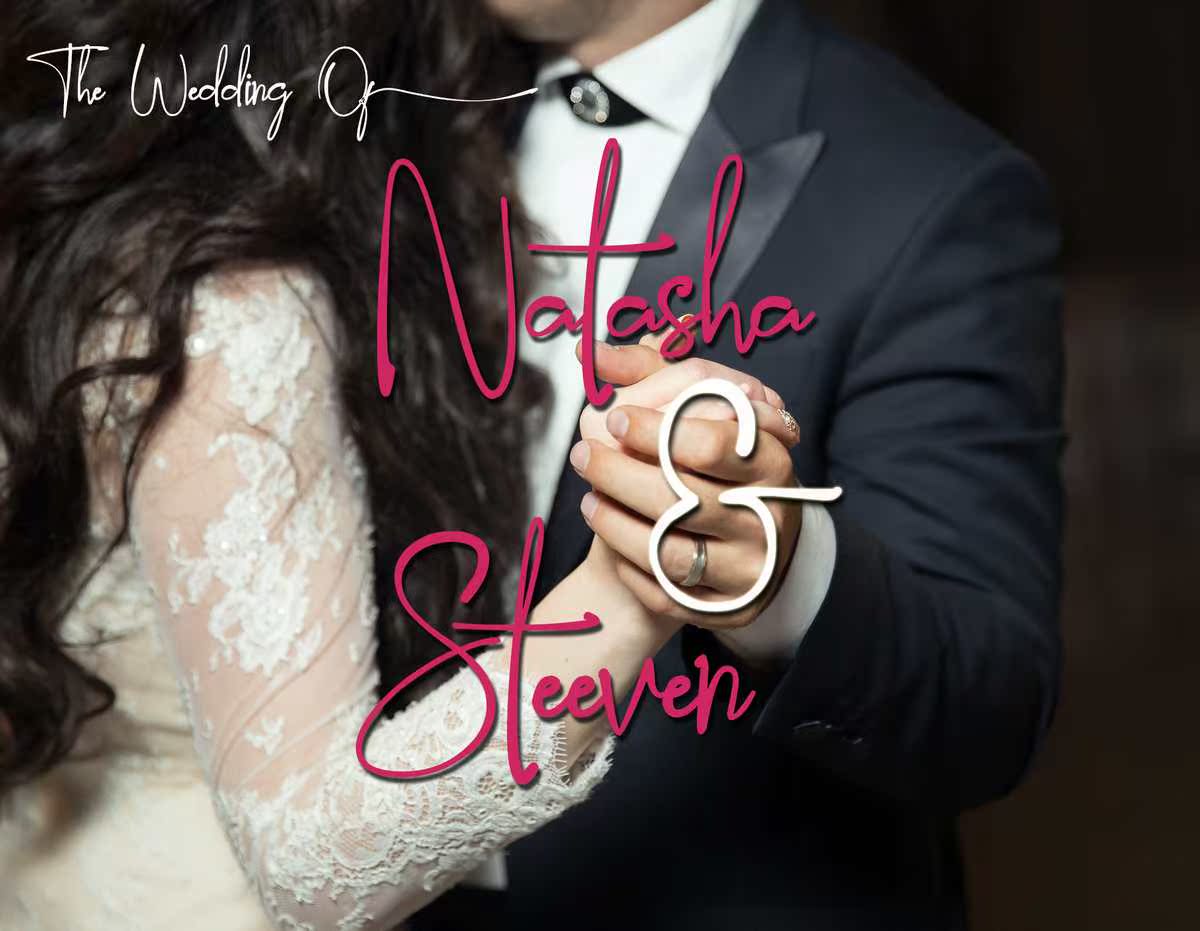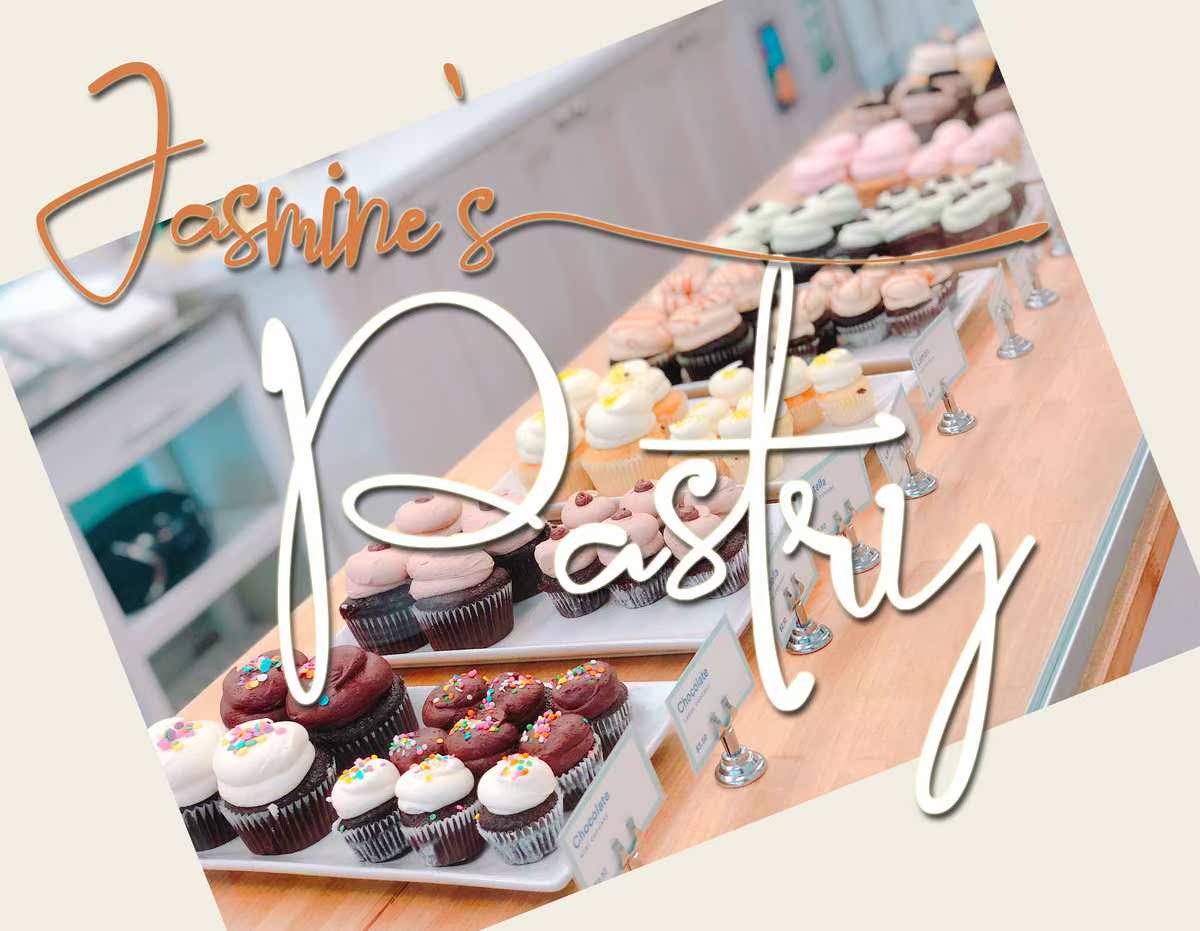
QuickyLove是由HizartDesign编写的现代手写字体。它可以准确地手写字母,让您的设计具有优美的文字,让您的设计更具吸引力。QuickyLove是徽标、贺卡、包装设计、耐磨性、工艺设计、任何项目、书名、婚礼宣传、包装的完美之选,还有更多。QuickyLove是由HizartDesign编写的现代手写字体。它可以精确地手写字母,让您的设计具有优美的文字,让您的设计更具吸引力。QuickyLove是徽标、问候卡、包装设计、耐磨性、工艺设计、任何项目、书名、婚礼宣传、包装等的完美之选。